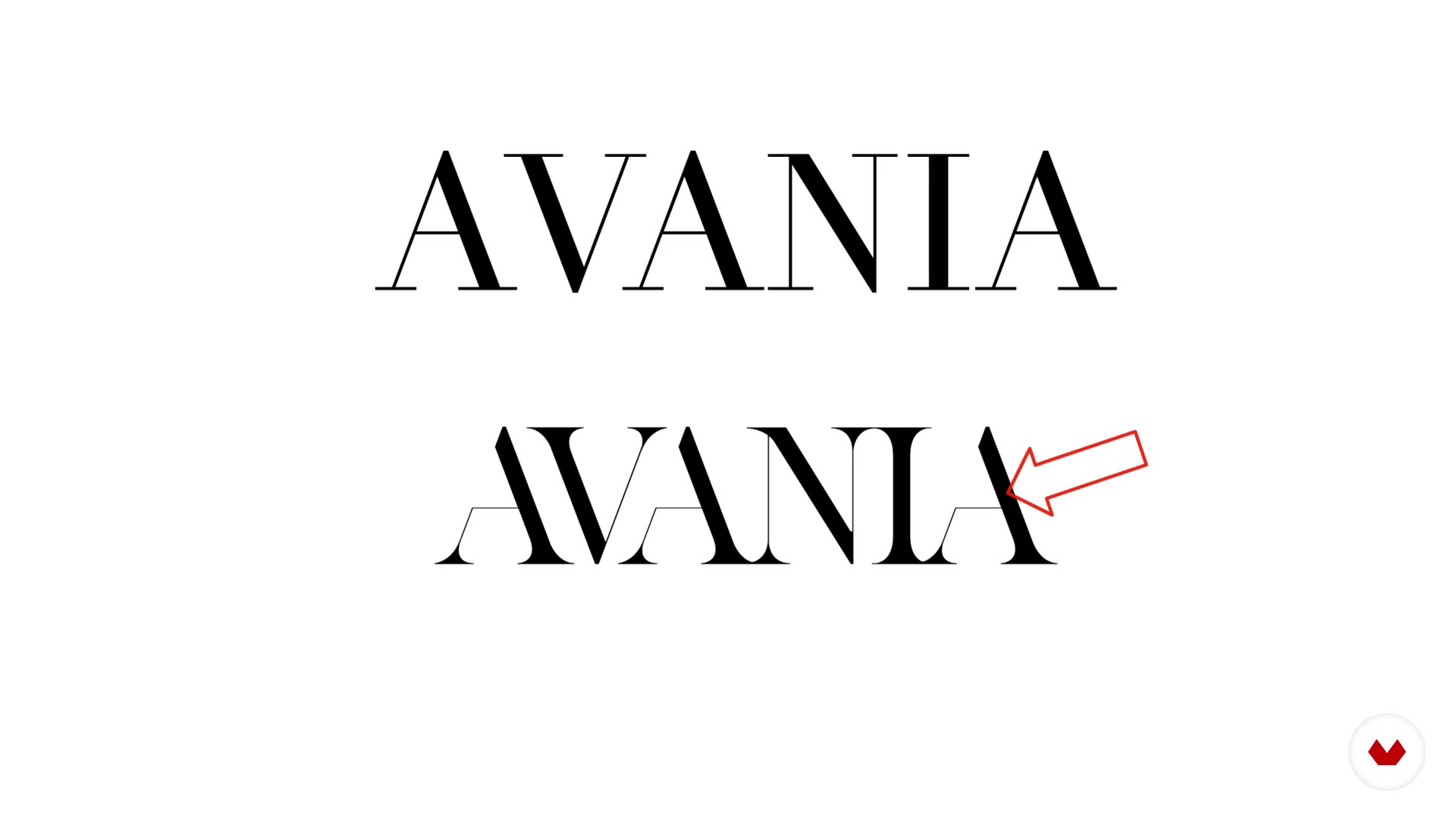
Personnalisation de polices de caractères pour création de logo
Comment manipuler les polices avec un but
À propos de la leçon : Comment manipuler les polices avec un but
“Maintenant, nous verrons l'importance de manipuler les polices dans un but précis. C'est-à-dire donner à un logo une particularité et une personnalité afin qu'il fonctionne comme un différenciateur sur le marché. ”
Dans cette leçon, Monotypo Studio aborde le sujet : Comment manipuler les polices avec un but, qui fait partie du cours Domestika en ligne : Personnalisation de polices de caractères pour création de logo. Apprenez le procédé de modification des polices pour construire une identité de marque unique.
“Dans cette leçon. nous verrons l'importance de manipuler des polices avec un FWIN. Ici. nous pouvons comme dans cet exemple particulier la descendante du Z. des concepts déjà vus dans la leçon passée. Et la... Jusqu'à l'ascendante du B sont manipulées. d'une manière qui génère un dynamisme dans la police et voici le résultat final. Ici. nous pouvons voir comment ce trait va donner une caractérisation très particulière à la police. que nous ne pourrions pas obtenir avec une police de stock standard de l'ordinateur. et la manipulation du réglage optique. Je vais vous montrer un autre exemple....”